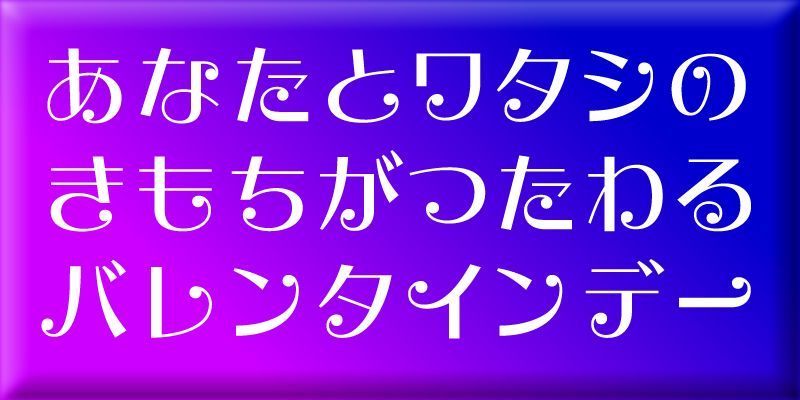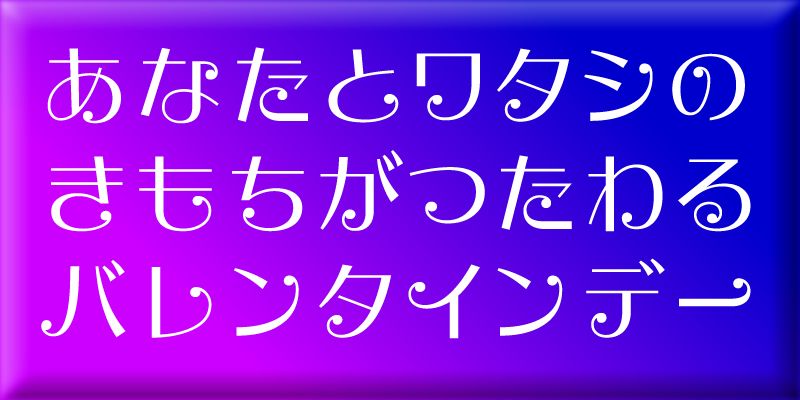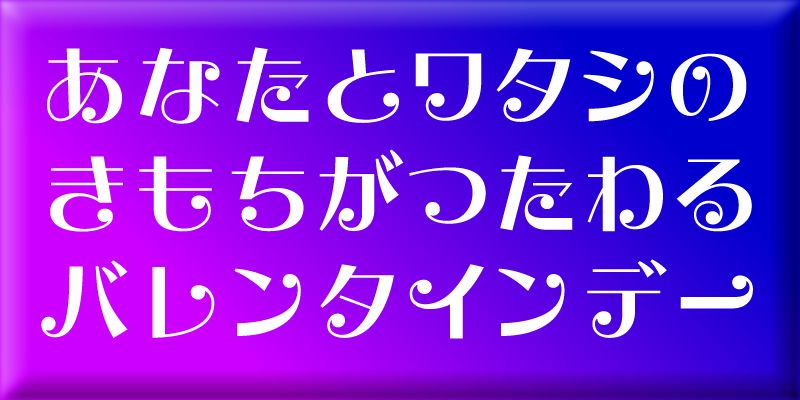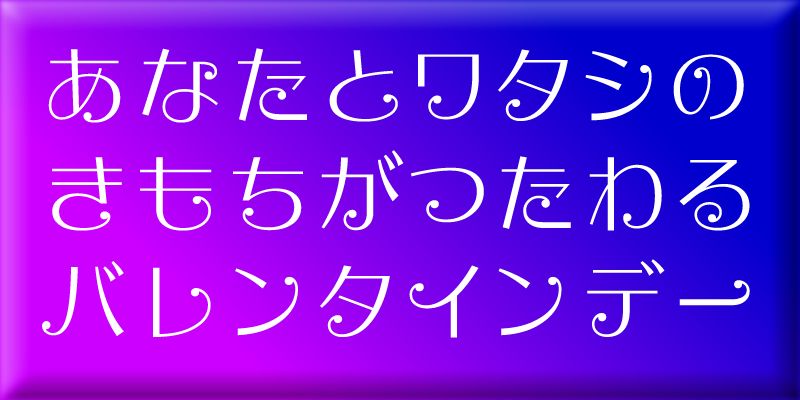
えれがんと-W3
文字の一部に丸いアクセントがついた、かなフォントです。
楽しそうでカワイイ雰囲気が、若い女性や子供たちに好まれています。
漢字は、源ノ明朝のRegular または、平成明朝のW3 がフィットすると思います。
えれがんと-W5
文字の一部に丸いアクセントがついた、かなフォントです。
楽しそうでカワイイ雰囲気が、若い女性や子供たちに好まれています。
漢字は、源ノ明朝のSemiBold または、平成明朝のW5 がフィットすると思います。
えれがんと-W7
文字の一部に丸いアクセントがついた、かなフォントです。
楽しそうでカワイイ雰囲気が、若い女性や子供たちに好まれています。
漢字は、源ノ明朝のBold または、平成明朝のW7 がフィットすると思います。
えれがんと-W9
文字の一部に丸いアクセントがついた、かなフォントです。
楽しそうでカワイイ雰囲気が、若い女性や子供たちに好まれています。
漢字は、源ノ明朝のHeavy または、平成明朝のW9 がフィットすると思います。